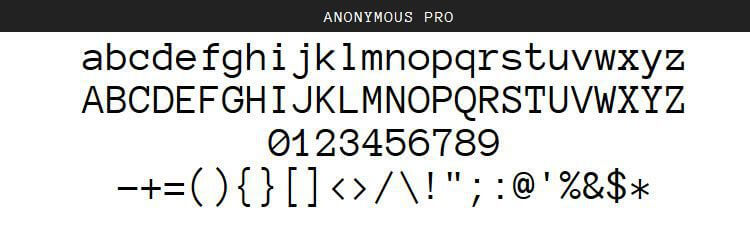
無料ダウンロードの等幅フォント18選 コーディング&プログラミングにおすすめ
コーディングに使用するフォントなど、今まで気にしたことのない方が多いでしょう。IDEのデフォルトで設定されている固定幅フォントに見慣れているのは、ある意味ラッキーかもしれません。
お気に入りのフォントが決まっているとしても、果たしてそれは、コーディングに一番ふさわしいと言えるでしょうか?フォント自体の良し悪しについては、基準がないのでここでは触れません。ちなみに私が使用しているのはUbuntuとMono Regularですが、これは各コーダーの好みによると言えます。ですが、プログラマーとコーダーのためにデザインされた無料フォントもあります。
今回は、プログラミングに特化した固定幅フォントのご紹介と、フォントを選ぶ際の基本ポイントについてお話ししたいと思います。
ところで、プログラミング用のフォントには一体何が求められていると思いますか?第一に、きちんと読みやすく、均等な余白が設けられていることです。当たり前ですが、拡大された文字とグリフがセットになっていることが重要です。また読みやすさよりも重要なのが、フォントが変わっても”1(イチ)”と”i(アイ)”と”l(エル)”の区別や、”o(小文字のオー)”と”0(ゼロ)”と”O(大文字のオー)”の区別がきちんと出来ることです。
Anonymous Pro by Mark Simonson (Regular, Italic, Bold, and Bold Italic)
Inconsolata by Raph Levien
Hermit by Pablo Caro (Light, Medium & Bold)
Edlo by Eric Hamiter
Meslo by André Berg (LG Small, LG Medium & LG Large)
Vera Sans Mono by Bitstream (Roman, Oblique, Bold & Bold Oblique)
Fira Mono by Mozilla (Regular & Bold)
PT Mono by Alexandra Korolkova (Regular & Bold)
Envy Code by Damien Guard (Regular, Italic & Bold)
Ubuntu Mono by Dalton Maag
Liberation Mono by Steve Matteson for RedHat
Fantasque Sans Mono by Jany Belluz (Regular, Italic & Bold)
Droid Sans Mono by Steve Matteson for Android
Consolas Mono by Microsoft
Drucifer Monospace by Drucifer
BPmono by Backpacker (Regular, Italic & Bold)
DejaVu (Regular, Oblique, Bold & Bold Oblique)
Monaco by Susan Kare and Kris Holmes for OS X